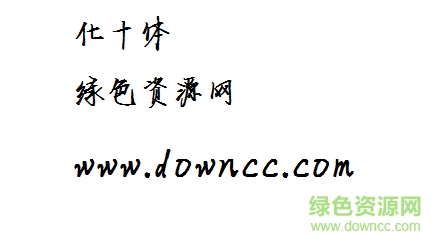
化十體是一款好看的中英文字體,字體藝術(shù)氣息十足,筆畫(huà)形如流水,整體效果非常優(yōu)美,喜歡這款字體的朋友歡迎到綠色資源網(wǎng)下載使用!
化十體字體是一款應(yīng)用于藝術(shù)設(shè)計(jì)方面的英文字體,該字體筆畫(huà)正規(guī),可以廣泛應(yīng)用于名片設(shè)計(jì)、新聞媒體、宣傳海報(bào)、ppt、影視制作以及內(nèi)容用字等領(lǐng)域。